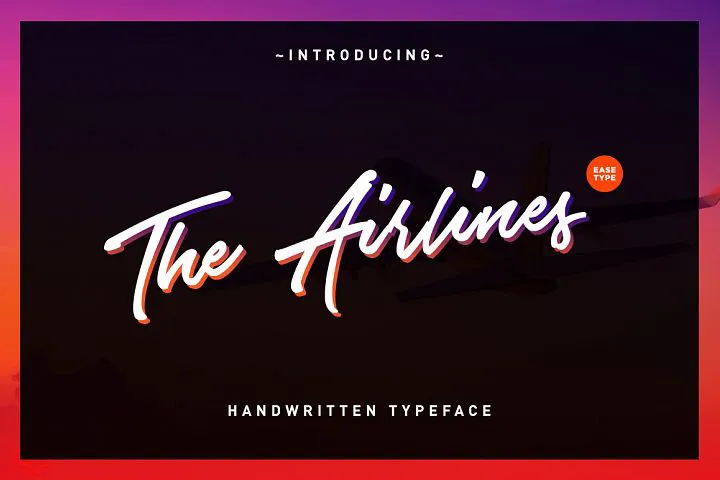
The Airlines Script Font – Download Grátis
Aqui está uma descrição em português para a página de download da font ‘The Airlines Script Font’, adaptada ao estilo solicitado: Esta fonte script moderna e elegante é perfeita para quem busca uma tipografia sofisticada com um toque de personalidade. Criada pela designer 178-MC, The Airlines atua como um aliado eficaz para projetos de branding, desde criação de logos até a design de websites, oferecendo uma combinação perfeita de estilização e funcionalidade. Com linhas limpas e formas fluidas, esta fonte é ideal para criar designs autênticos com letras escritas à mão. Suave como um contorno, ela se destaca em projetos de logomarca ou qualquer outro tipo de projeto que exigirá uma cara única e profissional. O estilo clean da The Airlines Script Font combina perfeitamente com o desenho detalhado dos aeroportos, tornando-a uma escolha excelente para aquelas empresas que usam o setor aéreo em suas identidades visuais. Agora, sem custo adicional, você pode ter acesso à The Airlines Script Font. Com sua facilidade de uso e aparência impecável, ela é perfeita tanto para projetos impressos quanto para websites modernos. Inove seu design corporativo com The Airlines!